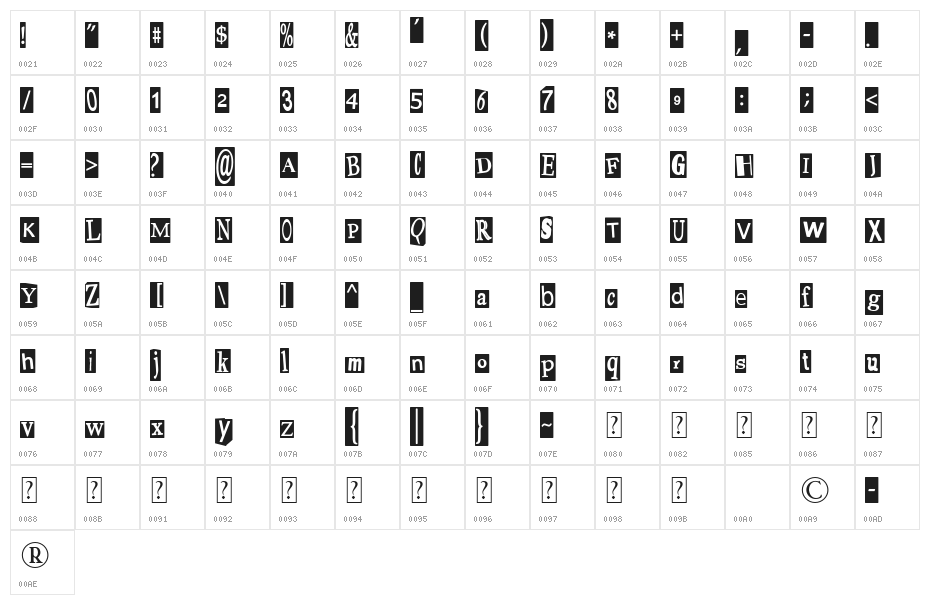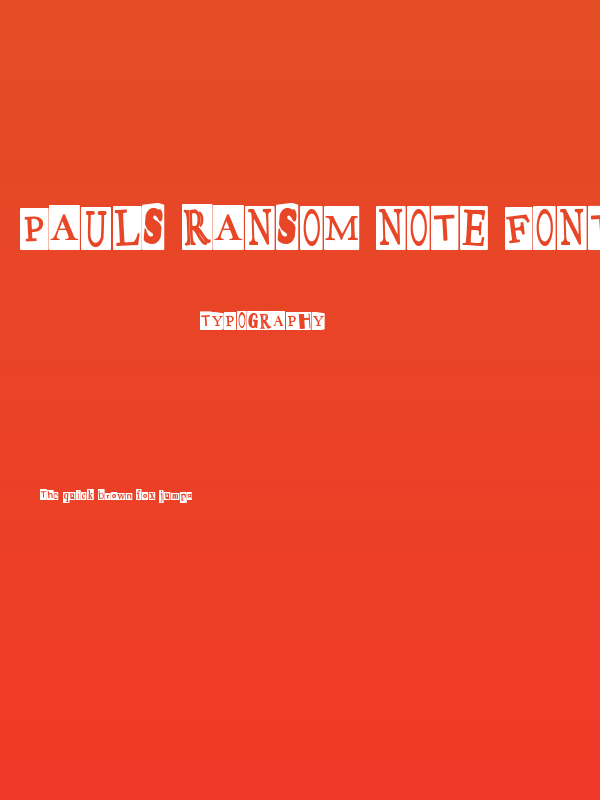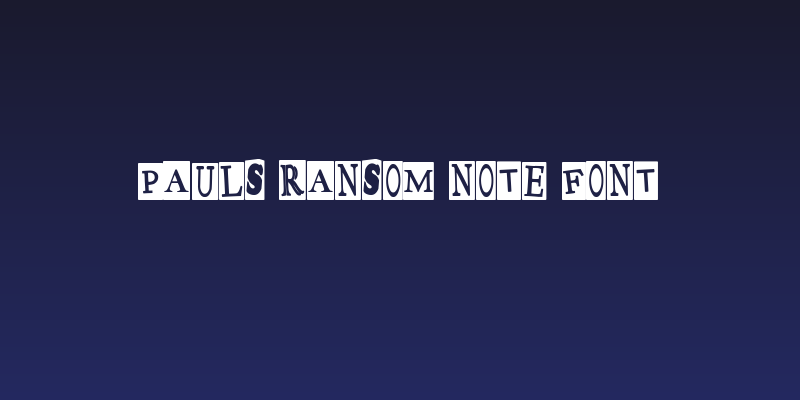
Pauls Ransom Note Font Font
| Cas d'utilisation | Headlines, Posters, Creative Designs |
| Projets proposés | Ideal for creative projects such as posters, album covers, Halloween invitations, and any design needing a quirky, mysterious touch. |